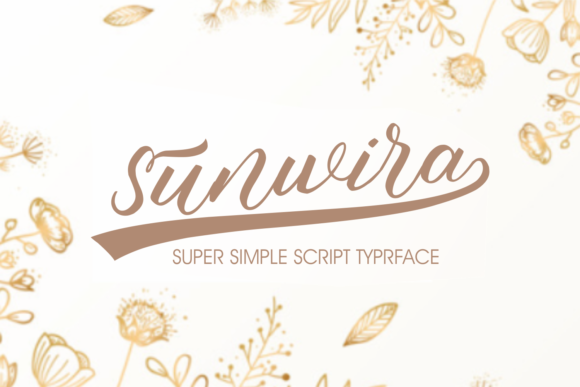
Creativefabrica Sunwira Font
[Creativefabrica] Sunwira Font
Sunwira - это прекрасный, классический и хорошо сбалансированный шрифт.
Он может быть использован для различных творений, требующих тонкого, индивидуального подхода.